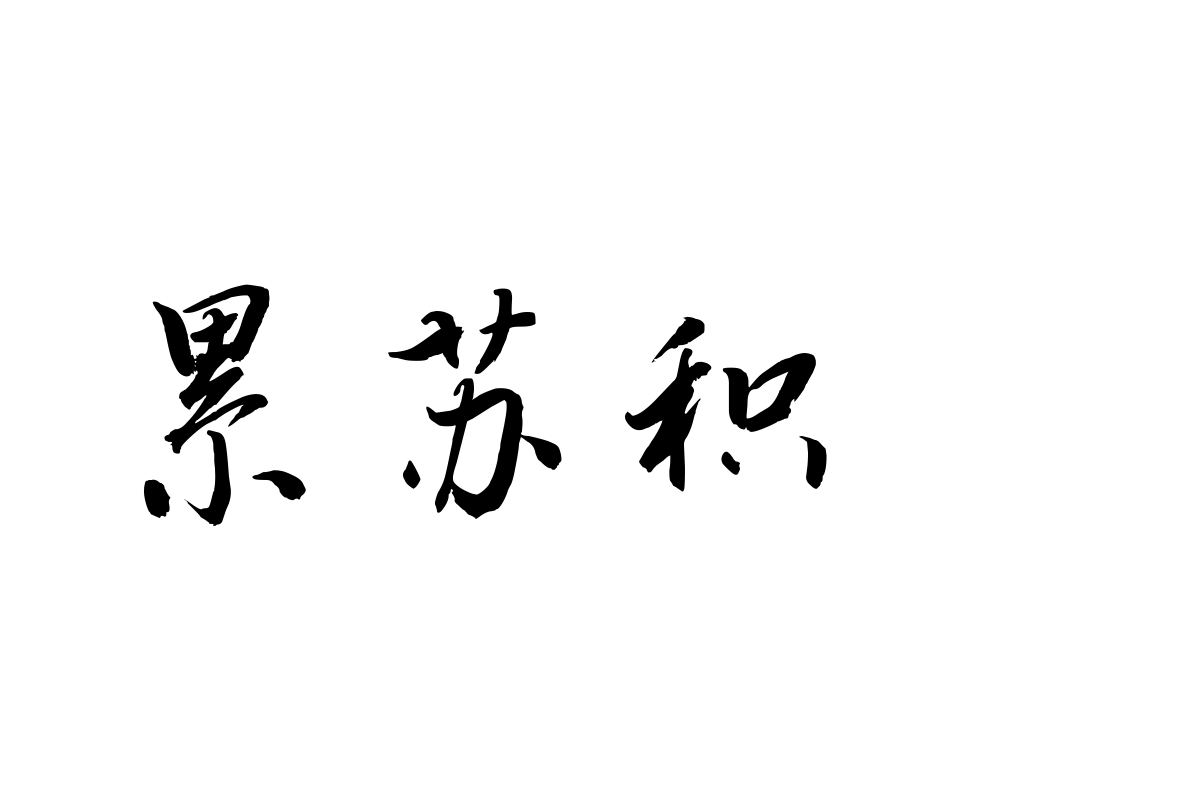
三极楚遥行楷字体是一款由北京华文时代科技有限公司开发的中文字体,具有独特的风格和特点。
首先,三极楚遥行楷字体的字形结构紧凑,笔画流畅,给人一种简洁明快的感觉。这种字体适合用于标题、正文等需要突出重点的场合。
其次,该字体的笔画粗细适中,既不过于纤细也不过于粗壮,使得整体视觉效果更加和谐。同时,字体的间距也恰到好处,不会显得拥挤或稀疏,有利于阅读和排版。
此外,三极楚遥行楷字体还具有一定的艺术感。它的笔画线条流畅自然,给人一种优雅、高贵的感觉。同时,字体的形态也具有一定的变化和多样性,使得整体视觉效果更加丰富。
总的来说,三极楚遥行楷字体是一款简约而不失美感的中文字体,适合用于各种场合的文本展示。